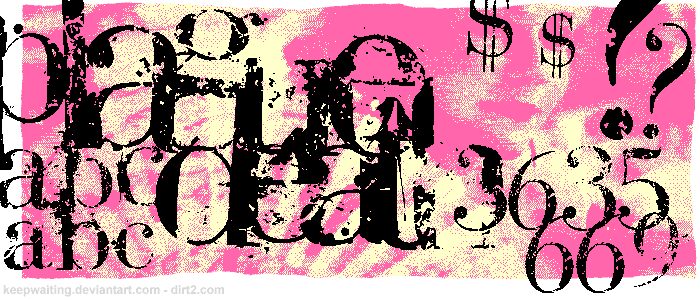
Bauer PlAGuE dEaTH di BauerBear è un font display con serif erose e gratuito, costruito su forme di lettere eleganti e ad alto contrasto con una rigorosa struttura editoriale di fondo, sottoposto a gravi danni superficiali. Curve sottili e serif taglienti rimangono visibili sotto bordi irregolari e sfrangiati, sbavature simili a inchiostro, macchie sparse e ampie zone raschiate che conferiscono al carattere un aspetto fisicamente danneggiato.
La sua collocazione ideale è la copertina di un album, dove la collisione tra contrasto formale e texture abrasiva può sostenere la musica industrial, metal o sperimentale, ma lo stesso trattamento usurato si adatta anche a poster horror e grafiche per abbigliamento dark. Parla in modo diretto agli amanti della musica underground e dell'horror.